手写字体是一种用笔纯手工创作出来的一种文字,这种字体在中国汉字发展史来说是非常具有价值和意义的。汉字书法就是手写体的一种代表,能够展现汉字的灵魂。科技发达的今天,依旧有着众多的手写字体诞生。比较优美的手写字体有哪些呢?哪个平台可以下载呢?
第一,义启手写体。对传统的字体来说,无外乎那几种,包括黑体、楷书、隶书、草书、行书、宋体等等,他们有着各自的独特的特点。然而,还有一种字体,被称为手写体,这种字体的大小不一致,形态也不一样。今天介绍的则是义启字库的义启手写体,这款字体是以女孩子的笔记作为基础,假如了爽朗、天然以及以拙变巧。字体相对来说是比较潇洒自然的,并带有婉转的特色,没有一种刻意雕饰的。可以说,这款字体动如脱兔,静如处子,字与字之间浑然天成。
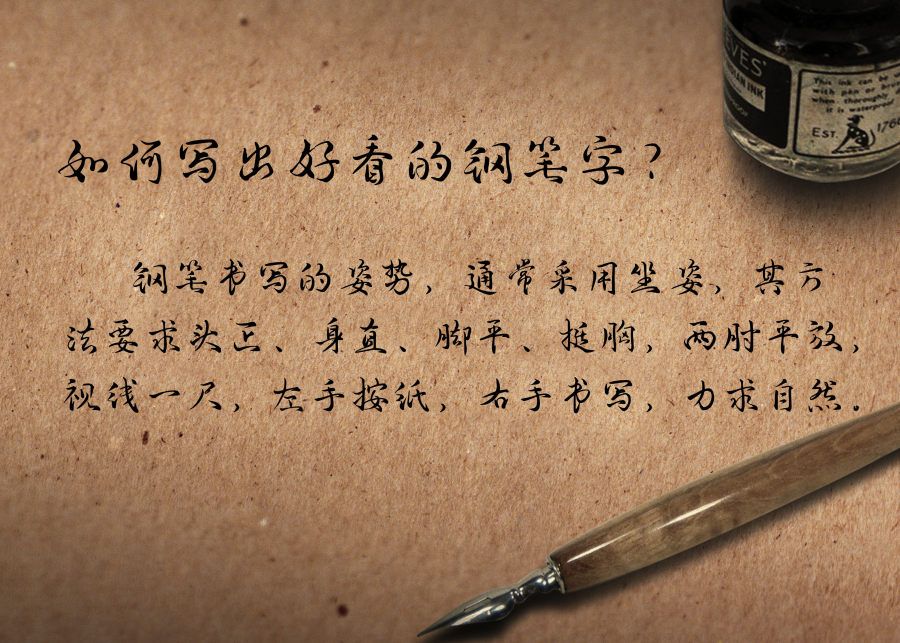
第二,义启萌雨体。这款字体是一种萌萌的字体,是义启字库中一款,富有个性化,比较适合小年轻和当前主流的年轻人的需求。作为一款手写体,它获得了众多小伙伴的喜欢。这也契合了年轻人追求个性,崇尚自然,不拘一格的个性。
第三,义启小楷书。楷书,是正儿八经的字体。义启字库当中有款小楷书,这款字体吸收了小楷的特性,创造出来的一款字体。书法字库在小的屏幕上是很难看出效果的,而义启小楷书恰恰弥补了这个缺陷。该字体主要是小字如大字,也就是小字有着大字的一种章法。经过修饰的笔画,使得字体变得圆润而又简洁,不至于便糊。可以说这款字体收放有度,气势如虹,有章有法。想要下载上面的字体可以登录字体视界,进行下载。